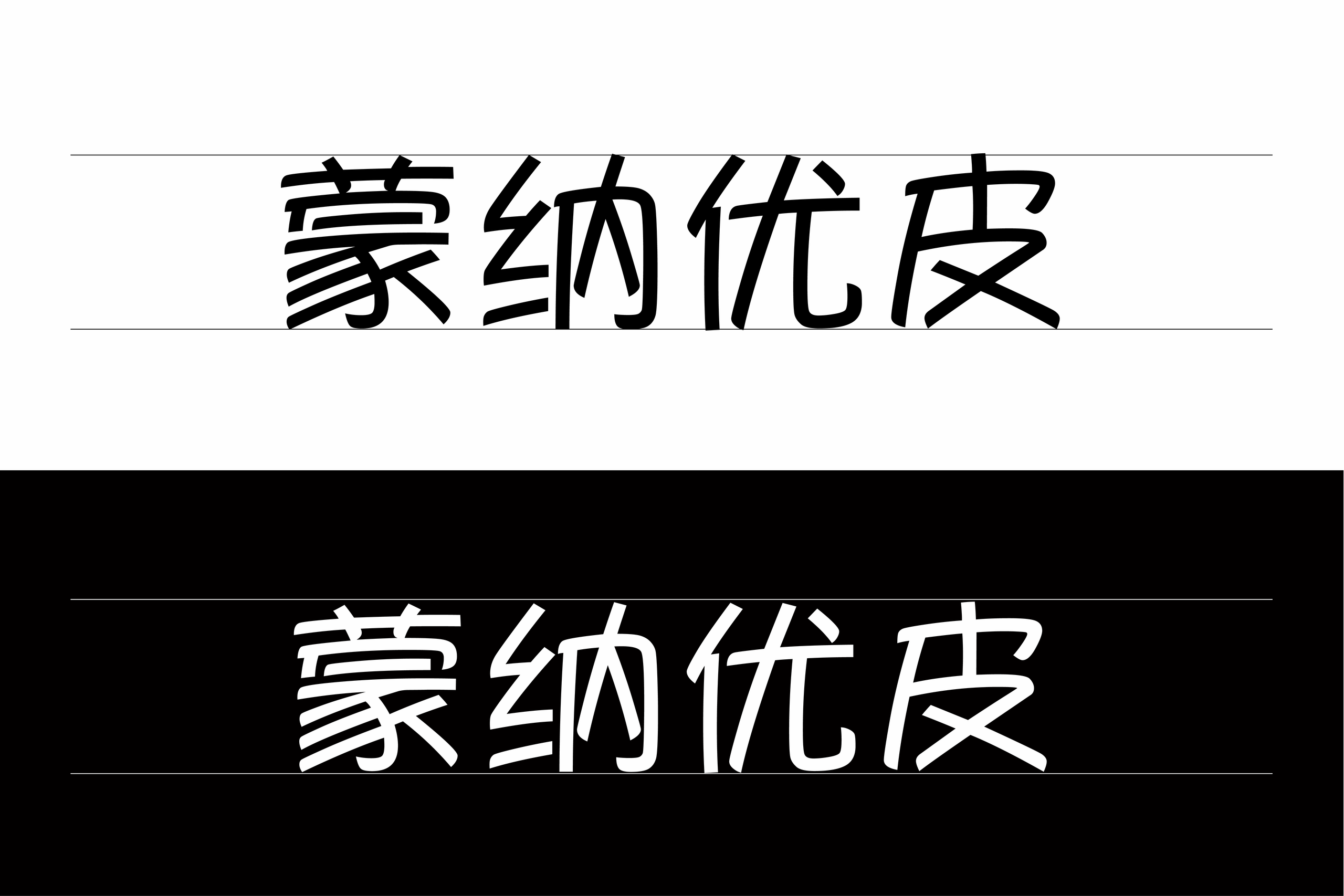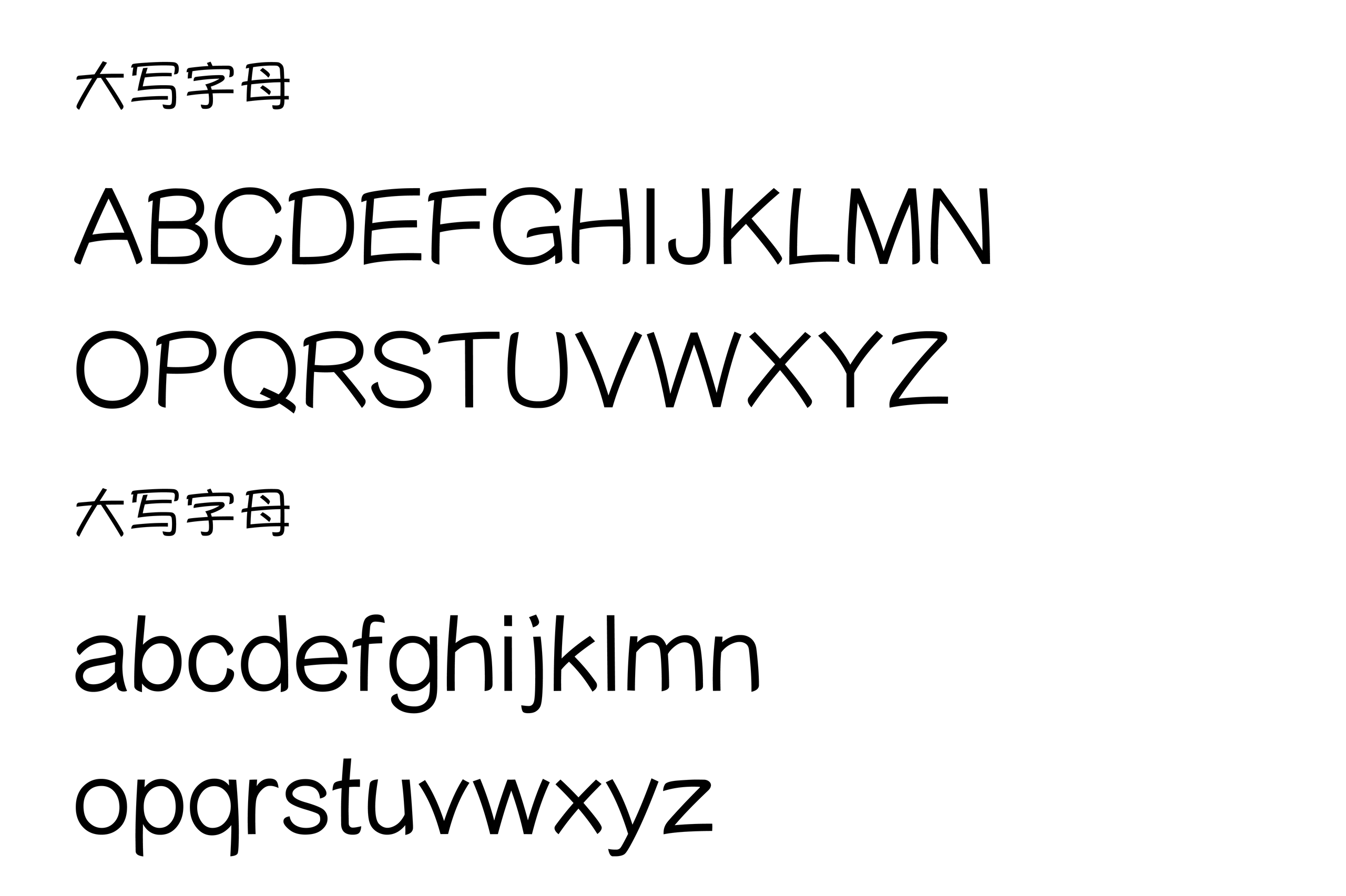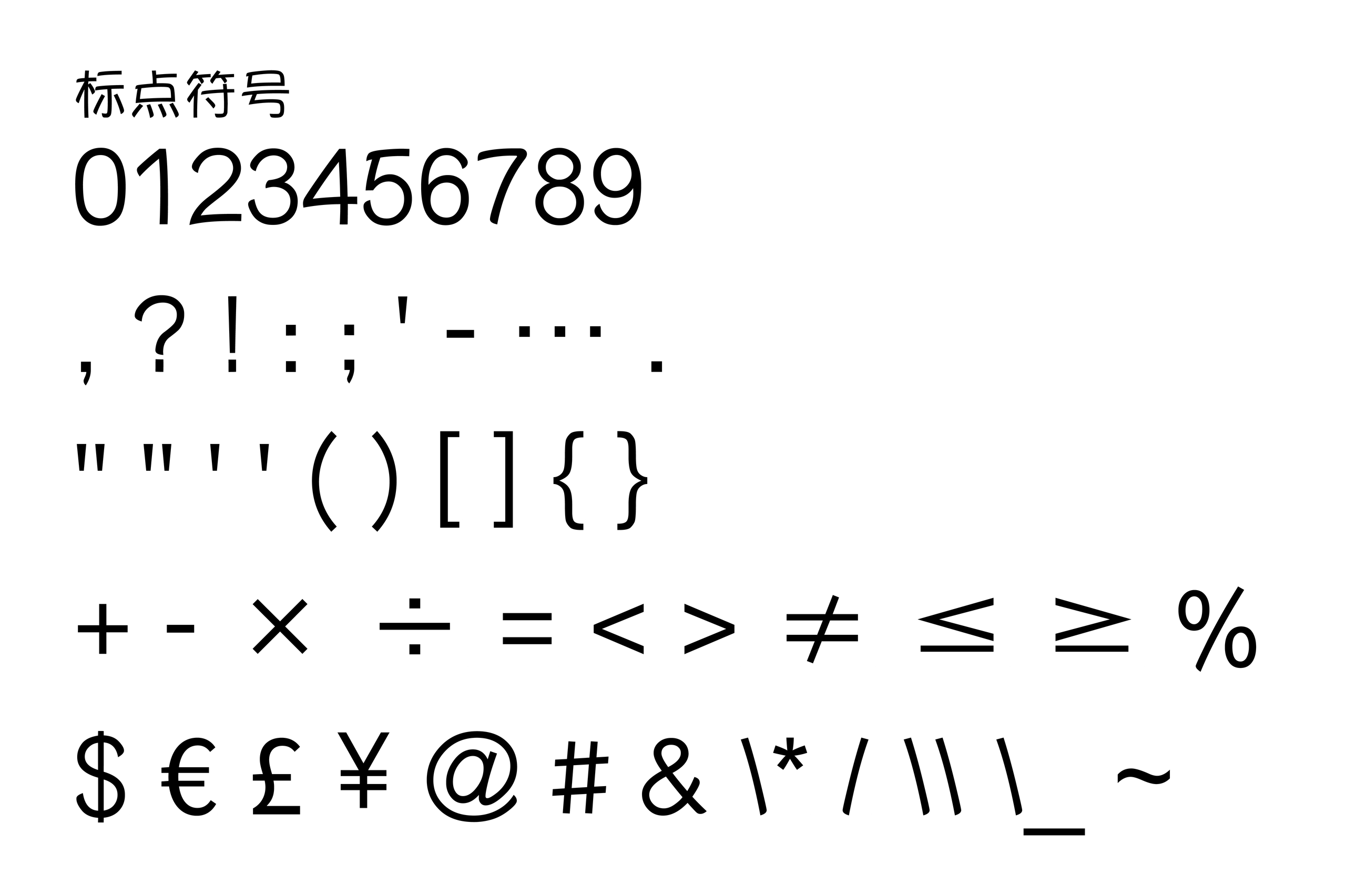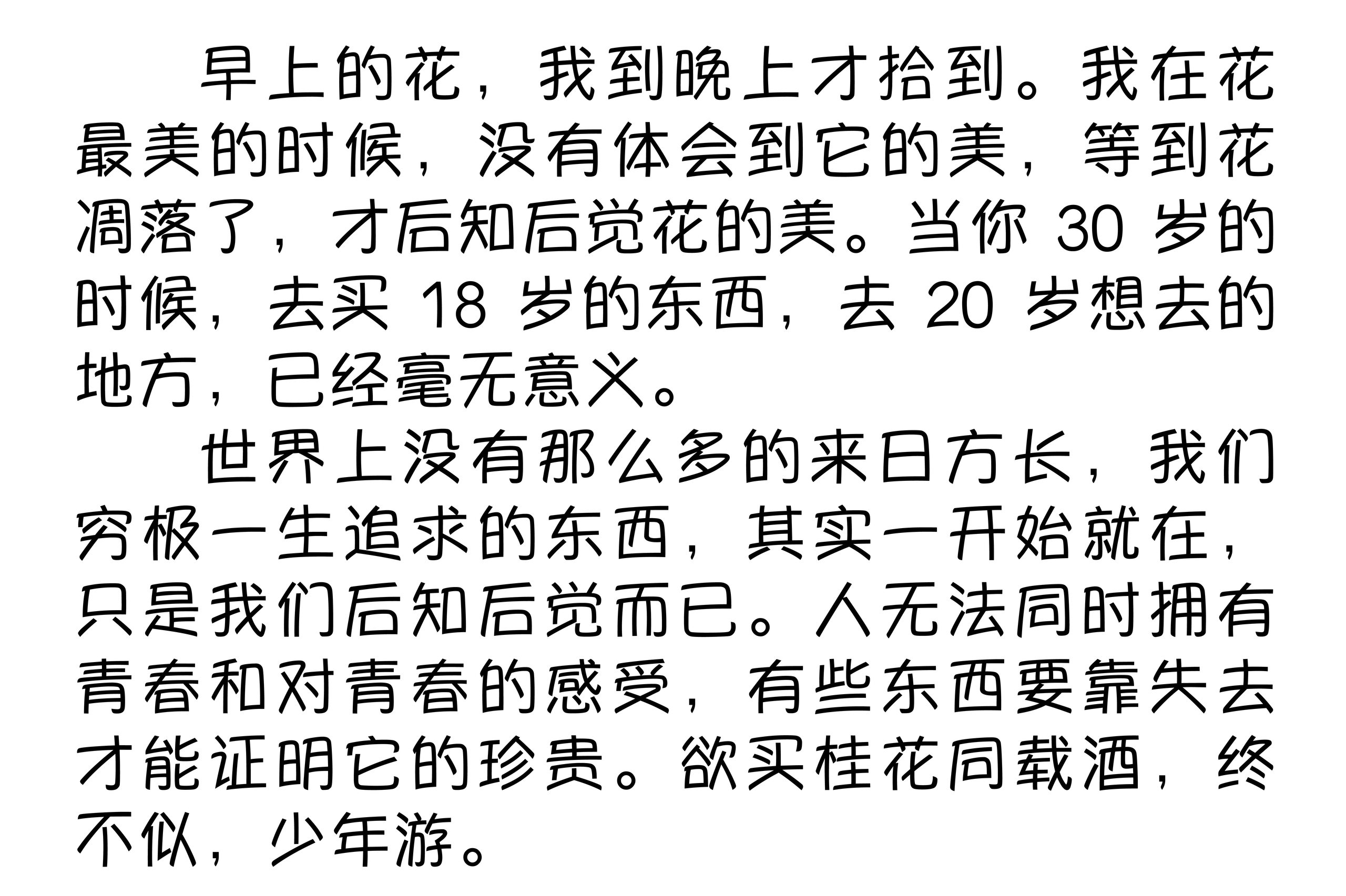
蒙纳优皮
MYuppy(蒙纳优皮)是一款诞生于移动互联网早期的简体中文字体,也是字体发展史中颇具代表性的一款开源字体。2010 年,Monotype Imaging Inc.(蒙纳影像)作为塞班基金会成员,将 MYuppy 捐赠并公开发布,其中 MYuppyGB-Medium 面向当时的移动设备及软件开发场景使用,是一款具有时代背景的中文数字字体。
从字形设计来看,MYuppy 并没有采用传统印刷字体较为规整的造型,而是将手写笔触与现代印刷字形结构结合起来。字体整体线条简洁、轻盈,部分笔画带有明显的手写感,同时通过开放的字形结构和相对均衡的比例保持文字的辨识度。这样的设计使它在具有个性化视觉特征的同时,并没有牺牲基本的阅读体验。
MYuppy 的字形尤其适合体现早期移动互联网产品的视觉气质。字体在设计之初便考虑到手机屏幕这一使用环境,通过较为清晰的笔画关系和开放的内部空间,使文字在较小字号及低分辨率屏幕中依然能够保持较好的可读性。因此,它不仅具有一定的字体设计价值,也记录了智能手机普及初期中文数字排版的发展特点。
在西文部分,MYuppy 同样延续了中文字体的整体设计思路。大写字母采用较为纤细的线条和简洁的几何结构,小写字母则具有更加明显的手写与现代无衬线特征。数字及标点符号也保持了相对统一的视觉风格,与中文字符组合时不会产生过于明显的风格割裂。
MYuppy 的诞生也与当时的塞班移动生态密切相关。2010 年前后,塞班系统仍是全球重要的移动操作系统之一,中文字体资源对于中国市场的手机系统和应用开发具有实际需求。Monotype Imaging 将 MYuppy 提交至塞班基金会开源体系,使 OEM 厂商、开发者以及其他参与者能够围绕字体进行使用和定制,这也让一款商业字体设计机构参与制作的中文字体以开源形式进入移动设备生态。
值得注意的是,网络上关于 MYuppy 的资料较为分散,部分字体名称容易造成混淆。此次介绍的 MYuppyGB-Medium 是 2010 年公开发布的版本,并不等同于 Monotype 后续商业字体产品中的 M Yuppy PRC(简优皮体)。此外,网络上还可以见到一些基于 MYuppy 制作的粗体或修改版本,例如 MYuppy-Bold-DDC 等,这些衍生文件也不应直接视为 Monotype Imaging 发布的官方原版。
总体而言,MYuppy 不仅是一款具有独特手写感的现代中文字体,更是一份来自早期智能手机时代的字体设计样本。它将传统文字结构与数字设备的显示需求结合起来,同时见证了 Monotype Imaging 与塞班开源生态之间的一次合作。对于需要复古移动互联网视觉、科技产品界面或具有早期数字时代气质的设计项目来说,MYuppy 依然具有一定的参考和使用价值。